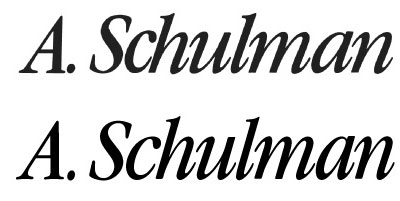
Kursive ... nur welche?
„Schriften sind für mich wie Gesichter.”
Dies habe ich aber scheinbar noch nie gesehen … trotzdem es mir bekannt vorkommt.
Hm, ich dachte gerade aus der Erinnerung (denn auch mir kommt das bekannt vor), es wäre die kursive ITC Garamond (condensed?). Ist es aber doch nicht (obwohl sehr nah dran).
Jau, die isset.
Die Condensed zumindest. Das „c” sieht ein bisschen anders aus (schmaler)
aber das liegt wohl am Schriftenhersteller.
Irgendwie muß ich an späte 70er oder frühe 80er Jahre denken, wenn ich die ITC-Garamond sehe.
Vielleicht stammt das Logo ja noch aus alter „Fotosatzzeit”.
Norbert Pautners Tipp „ITC Garamond condensed italic” war genau richtig.
Hier der Beweis (wie gesagt: das „c” sieht etwas anders aus):
Oben Muster, unten nachgesetzt.
Meine Garamond stammt von Linotype.